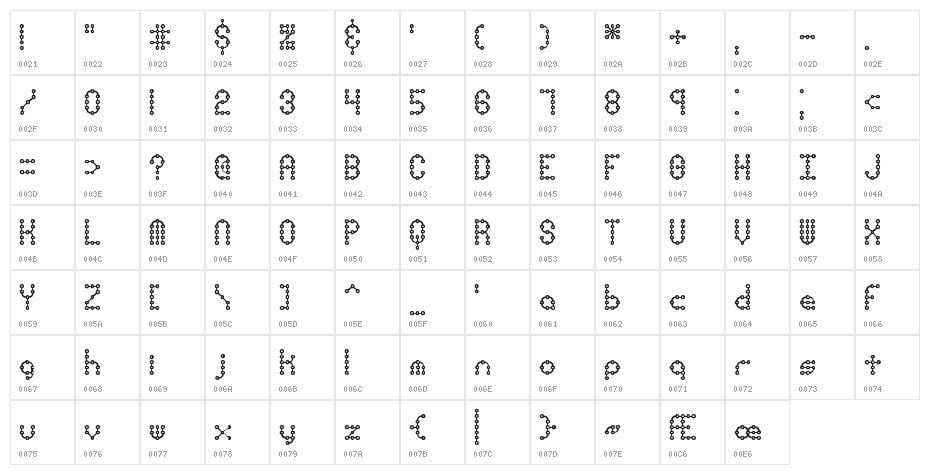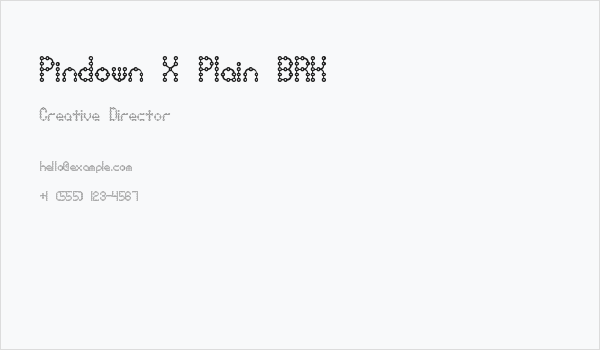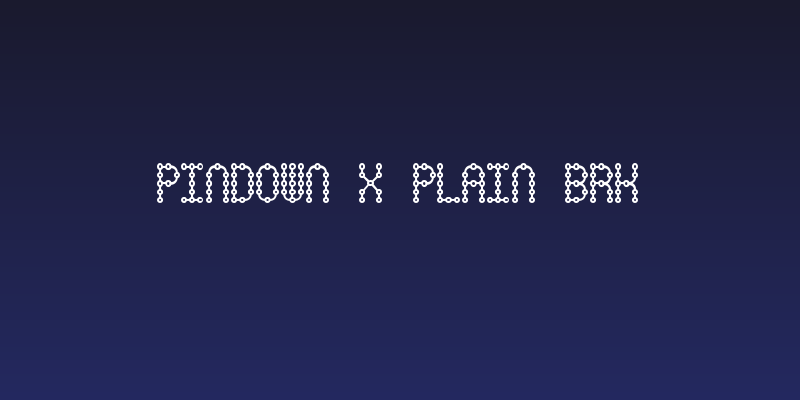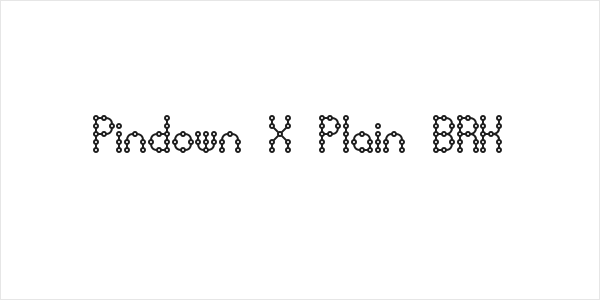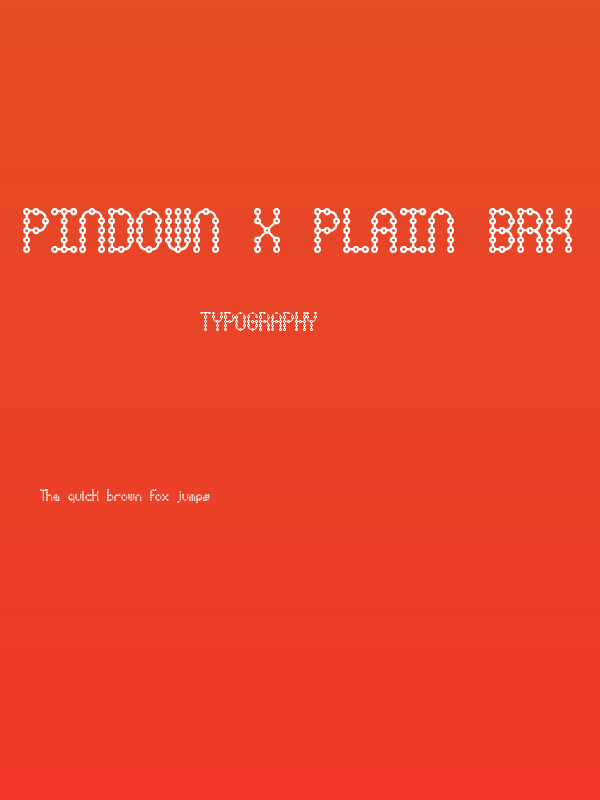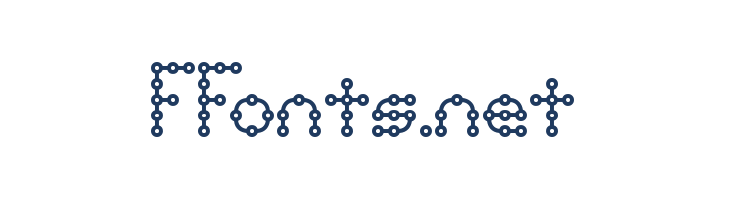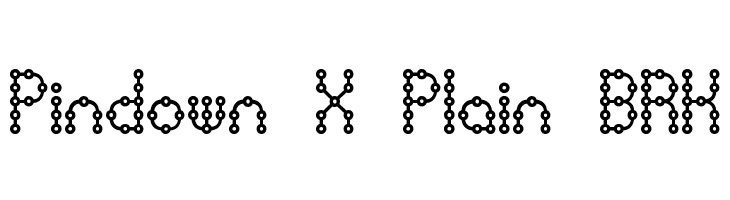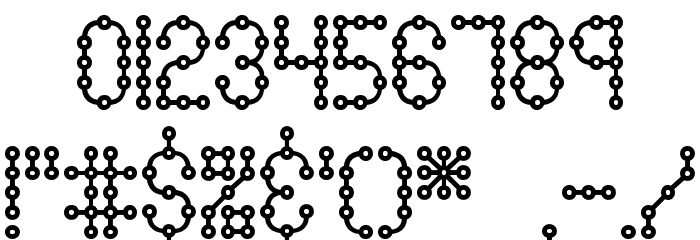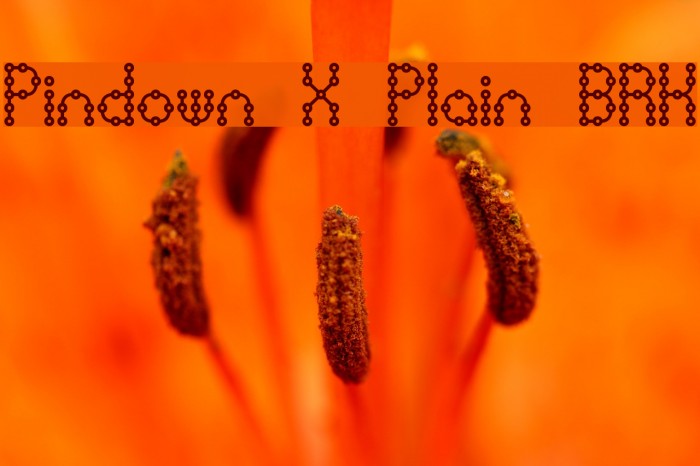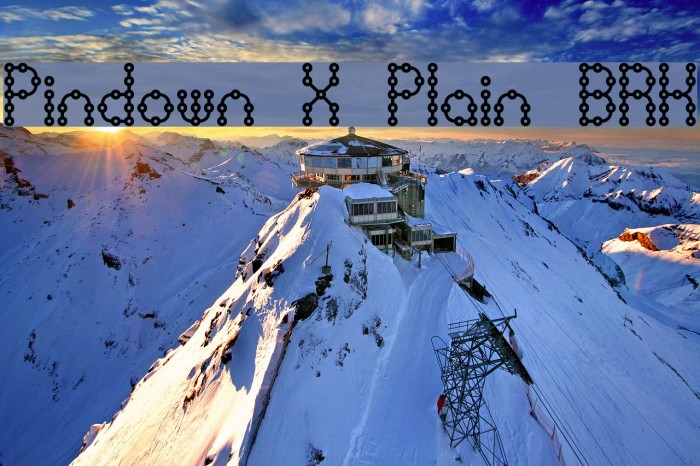
Pindown X Plain BRK Font
✎ Dotted
Fonts by www.aenigmafonts.com
| Vorgeschlagene Projekte | Ideal for children's books, playful branding, creative posters, and party invitations. |